個人利用可能なペン字フォントまとめ21種類
鉛筆やサインペンを用いて書いたような、手書き風のフォントを21種類紹介いたします。スーパーマーケットで見られるポップに近しいフォントもあります。ぜひフリーハンドで書いたような温かみのあるフォントをお探しください。
Mikiyu Font alphapen
みきゆフォントのアルファペンバージョン。
Touchpen Round
サインペンで書いたような味わい深い手書きの欧文フォント。
アームド・バナナ
筆ペン風フォント。第二水準までの漢字を収録。
あやせ
くるっとしたカーブが特徴的なフォント。
さなフォン
ちょっと細めの、サインペンとかボールペンで書いたような感じの書体。
さなフォン角
マジックで書いたような、POP風の書体。掲示用の文書やポスターなんかにおススメ。
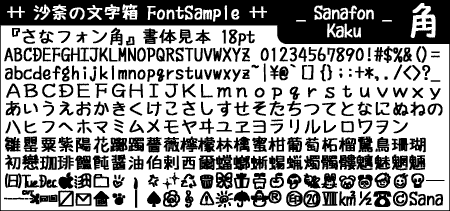
さなフォン丸
細めのマジックやサインペンで書いたような感じの、いわゆる丸文字フォント。
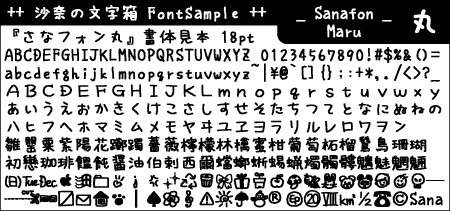
さなフォン型
POP風の書体「さなフォン角」を加工した2バイトTrueTypeFont(TTF)。
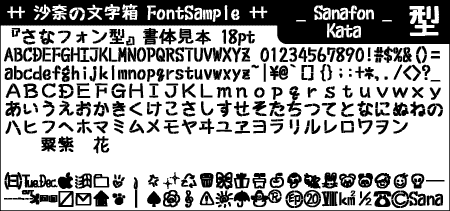
さなフォン悠
サインペンや細マジックで書いたような、ラフ書きの丸文字。
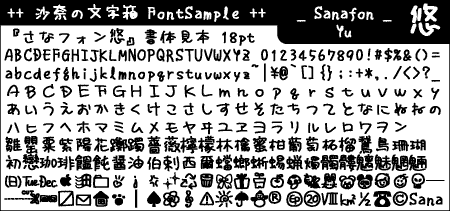
ジンペン糸-R
糸の刺繍のようなデザインのフォント。
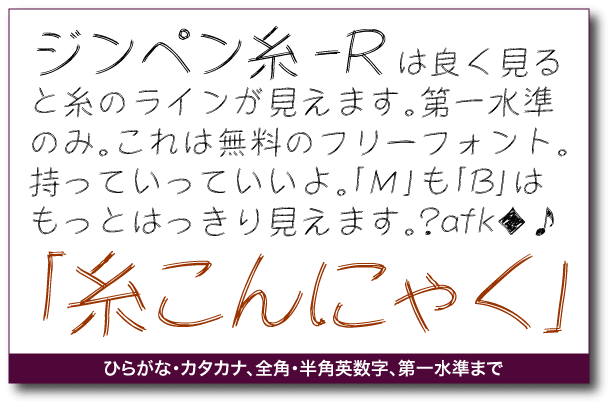
ジンペン毛羽-R
文字の端っこがケバケバしているフォント。
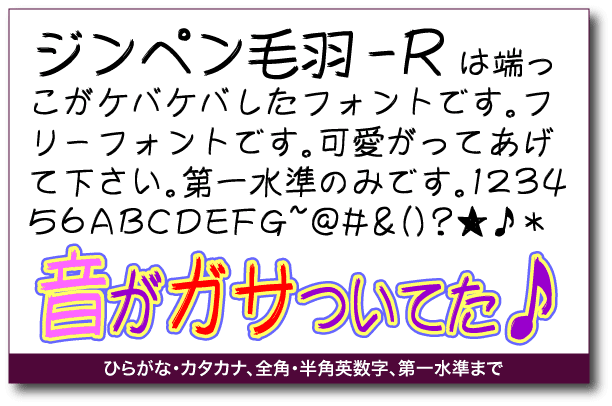
ジンポイント骨-R
文字の端に骨のイラストがデザインされたフォント。
セプテンバーL&M
細いペンを使って約8ミリの大きさにフリーハンドで描いた文字を元に作られたフォント。文字の輪郭は微妙にデコボコで手作りの風合いがでている。
たぬき油性マジック
普通紙に油性極太マジックで書いた手書き文字から作成された無料日本語フォント。年賀状やポップなどで手書きっぽさを出したいときにピッタリ。
ぷちはんど ほそぺん/ぷちはんど へなちょこほそぺん
作者様いわく「こだわりは、縦でも横でもへなちょこになること」とのこと。幼児の字を表現したい時などにどうぞ。
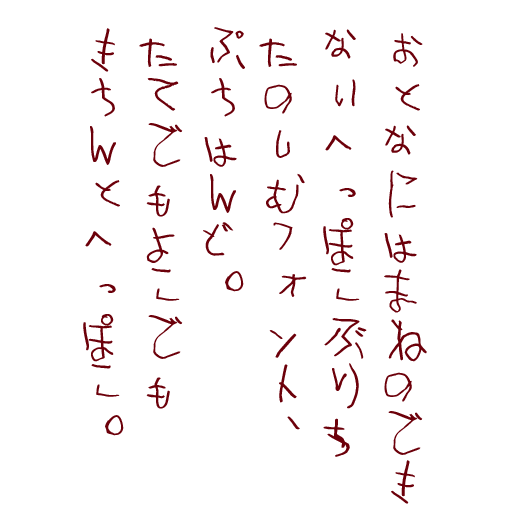
ふわふわフォント
ふわふわした雰囲気が漂う可愛いフォント。